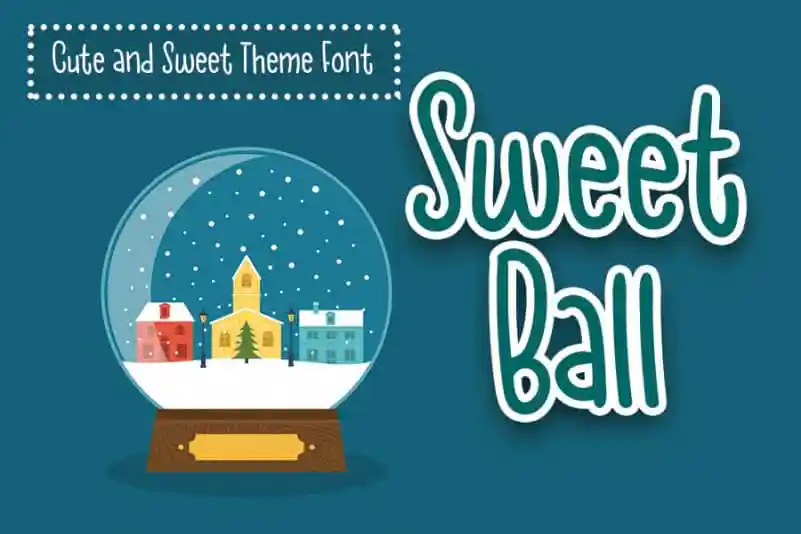
Sweet Ball Display Font – Download Grátis
A Sweet Ball Display Font é uma elegante abordagem para qualquer projeto que necessite de um toque alegre e autêntico. Embora possa parecer ser apenas uma fonte casual, ela carrega consigo uma graça e uma sinceridade irresistíveis, tornando-a a escolha perfeita quando se deseja adicionar um pouco mais de encanto ao design. Como um verdadeiro herói da infância nas letras, ela traz à tona uma atmosfera de brincadeira descontraída, adequada tanto para aplicativos digitais quanto para materiais impressos em formato de tela grande. Com sua caligrafia leve e colorida, esta fonte é ideal para gráficos online, banners ou até mesmo elementos de marca digital. É um recurso versátil que vai desde cartazes inspiradores até design de produtos pessoais, oferecendo uma maneira criativa de expressar alegria em qualquer projeto. Na categoria de Fonts Display, ela representa o equilíbrio perfeito entre personalização e impacto visual, deixando seu design mais divertido e agradável aos olhos do consumidor.